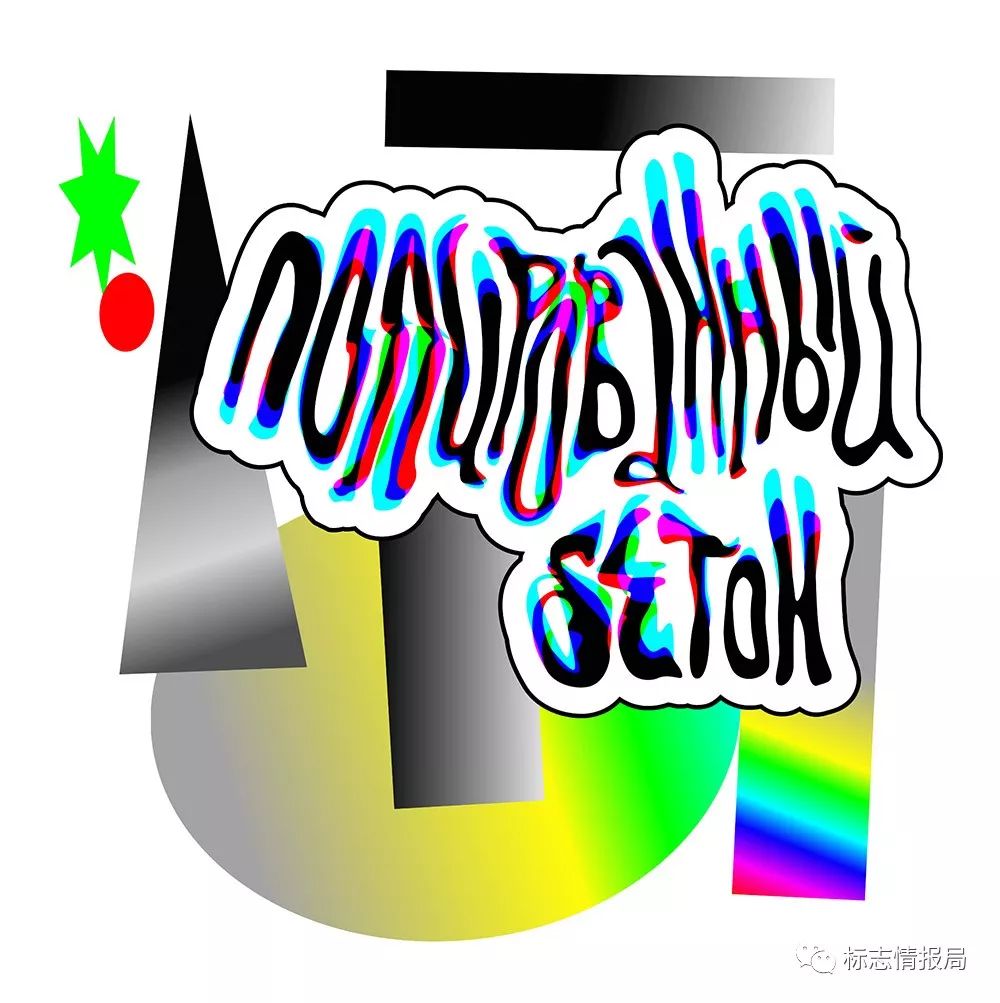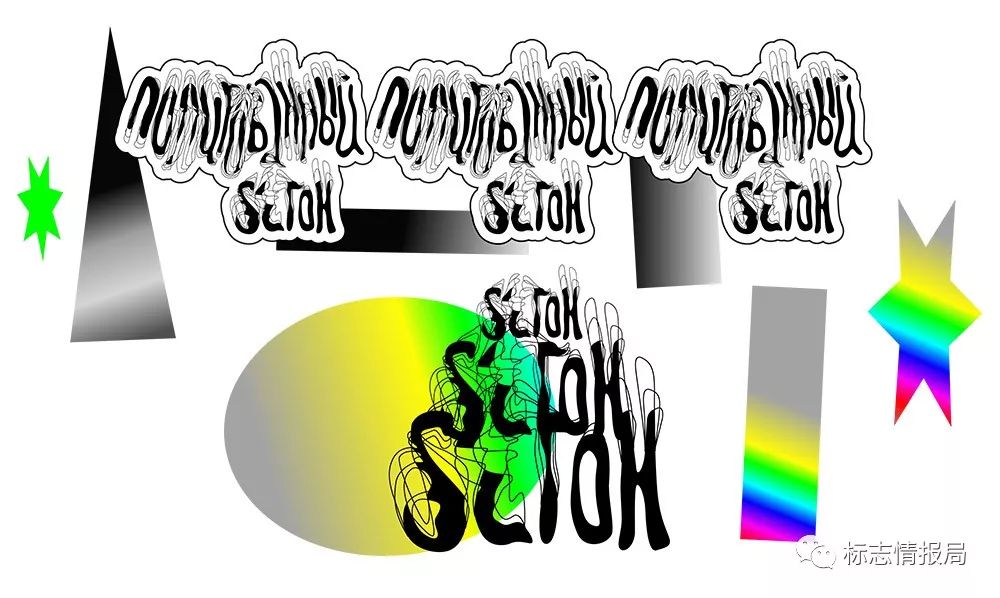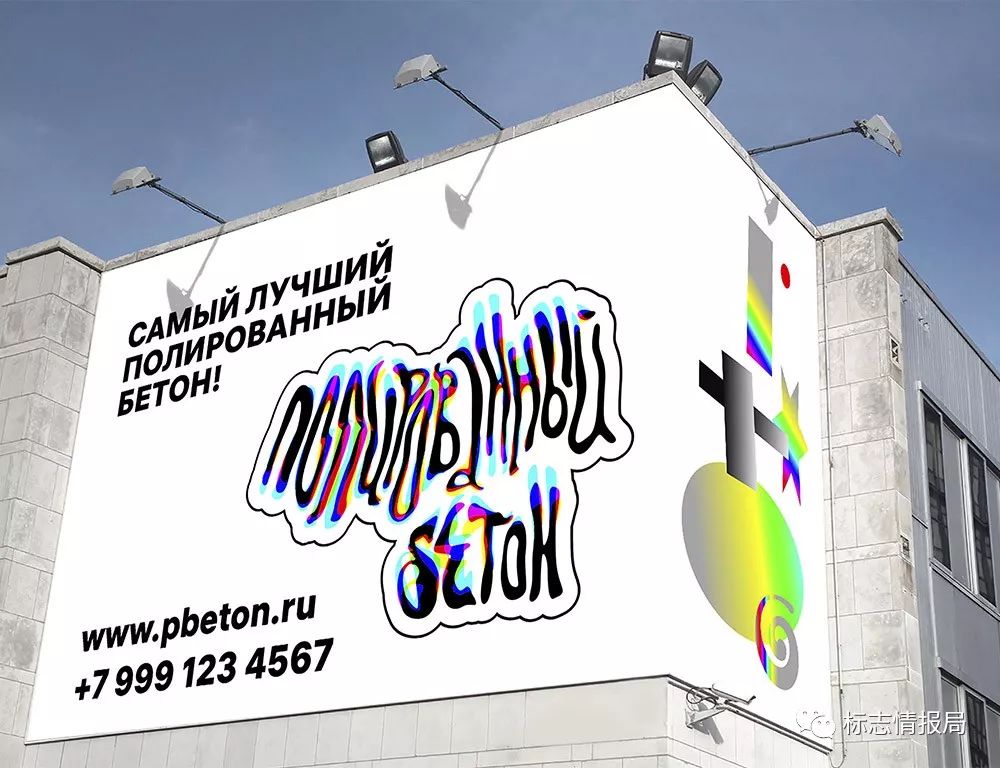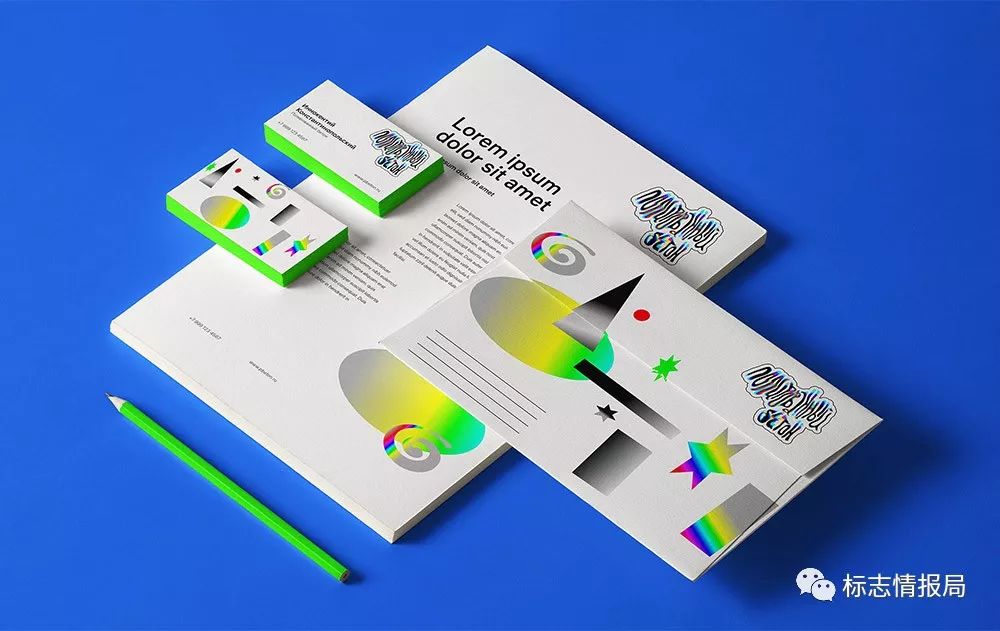
1w一个logo,可看完却怀疑人生……
提到Art.Lebedev Studio(下称Lebedev)这个名字,大家应该不会太陌生
它是俄罗斯最大的设计公司,1995年由Artemy Lebedev创立。
Art.Lebedev Studio
虽然是一家比较专业和成熟的设计机构
但是Art.Lebedev Studio也会经常做出一个常人难以理解的设计方案。
前不久,该机构摇滚乐队 Leningrad 设计的新 LOGO 因为融入生殖器元素而遭到大家的热议。
Lebedev 为列宁格勒设计的新LOGO
2018年,该公司为一家面包店设计的LOGO引来了大批网友的嘲笑和恶搞。
以至于很多人开始质疑Lebedev拿着自己专业的设计招牌来忽悠这些创业者。
Lebedev 为“Булочная(面包店)”设计的新LOGO
搞笑的是,这家公司去年为乌克兰国立歌剧院“强行”设计LOGO。
最后歌剧院跳出来说并没有邀请这家公司为其设计LOGO
同时也不会采用他们的设计方案。
Lebedev 为乌克兰国立歌剧院设计的新LOGO(图右)
Lebedev 为乌克兰国立歌剧院设计的新LOGO
当然,Lebedev 的实力的不可置疑的,他们为俄罗斯超级联赛设计的新LOGO和吉祥物就获得了大量的好评。
Lebedev 为俄罗斯奥委会设计的新吉祥物:帽子猫和不倒翁熊
同时,Lebedev 还为俄罗斯超级联赛、莫斯科地铁、莫斯科大剧院以及卢比货币的新符号等提供设计服务。
Lebedev 为俄罗斯超级联赛(RFPL)设计的新LOGO
Lebedev 的更多作品
今天的重点来了!
最近,Lebedev 又出神作了!一家来自俄罗斯的装饰混凝土地板公司Полированный бетон前不久找到了Lebedev ,希望希望这家专业的设计机构能够为自己的公司设计一个全新的LOGO。
Lebedev 随后分配两位设计师,耗时33天,为这家装饰混凝土地板公司打造了一个全新的LOGO设计,如上图。看的不够清晰?下面来张高清图:
俄罗斯的装饰混凝土地板公司LOGO
没看错,这是个LOGO,LOGO本身除了文字,其他元素看起来令人难以理解。PS预设的渐变色加上歪歪扭扭的俄文名字,给人的第一感觉好像是一个PS初学者刚刚打开软件练习的结果。
不过Lebedev 并没有觉得自己的作品在视觉上非常的难看或者“丑”,反而,他在项目展示页面是这样描述的:“优秀的标志会闪闪发光”。
负责该项目的艺术总监Artemy Lebedev表示,这种表现手法重新定义了平面设计,这将是品牌形象设计未来的趋势。他还暗示如果有人不喜欢这个作品,问题(显然)是在那个人身上,而不是在LOGO中。
应用展示
为什么Lebedev 会产出一些比较奇怪的设计?
其实较早前,Lebedev 推出了“快餐设计”服务,如果一家初创公司或者小企业没有多少预算放在形象的设计师,那么可以支付10万卢布(约合1万人民币,而且不可以退款),然后就可以找到这家知名设计公司为其设计LOGO。
Lebedev的设计师会抽空,一般在周末会为客户设计一个标志方案。
当然,Lebedev 的“快餐设计”所出的方案并不是完全都长这样,好不看好一般要看设计师当时的心情了。更佩服的是,人家买稿的能力。
试想一下,如果您的客户花一万块钱让你设计LOGO,一个月后,你发过去的方案是这样的,那会发生什么有趣的事情呢?